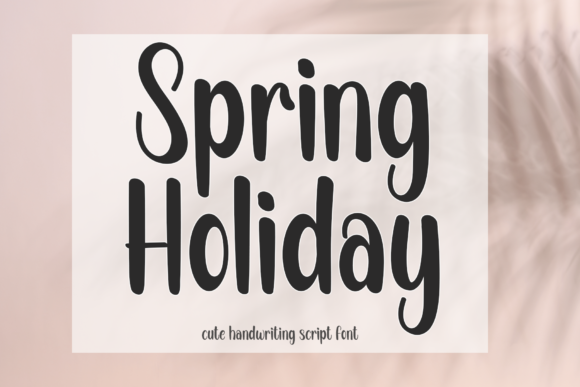
Spring Holiday
หากคุณกำลังมองหาเนื้อหาคุณภาพสูงเช่น Spring Holiday แพ็คเกจพรีเมียมนี้เป็นตัวเลือกที่ยอดเยี่ยมสำหรับโปรเจ็กต์สร้างสรรค์ของคุณ
สร้างขึ้นอย่างแม่นยำ Spring Holiday ให้เวกเตอร์ที่สะอาด พิมพ์ตัวอักษรที่ราบรื่น และใบอนุญาตเชิงพาณิชย์เพื่อความสบายใจ
ไม่ว่าคุณจะสร้างผลิตภัณฑ์ POD (Print on Demand) คำเชิญงานแต่งงาน หรือกราฟิกโซเชียลมีเดีย Spring Holiday ก็เหมาะสมอย่างยิ่ง